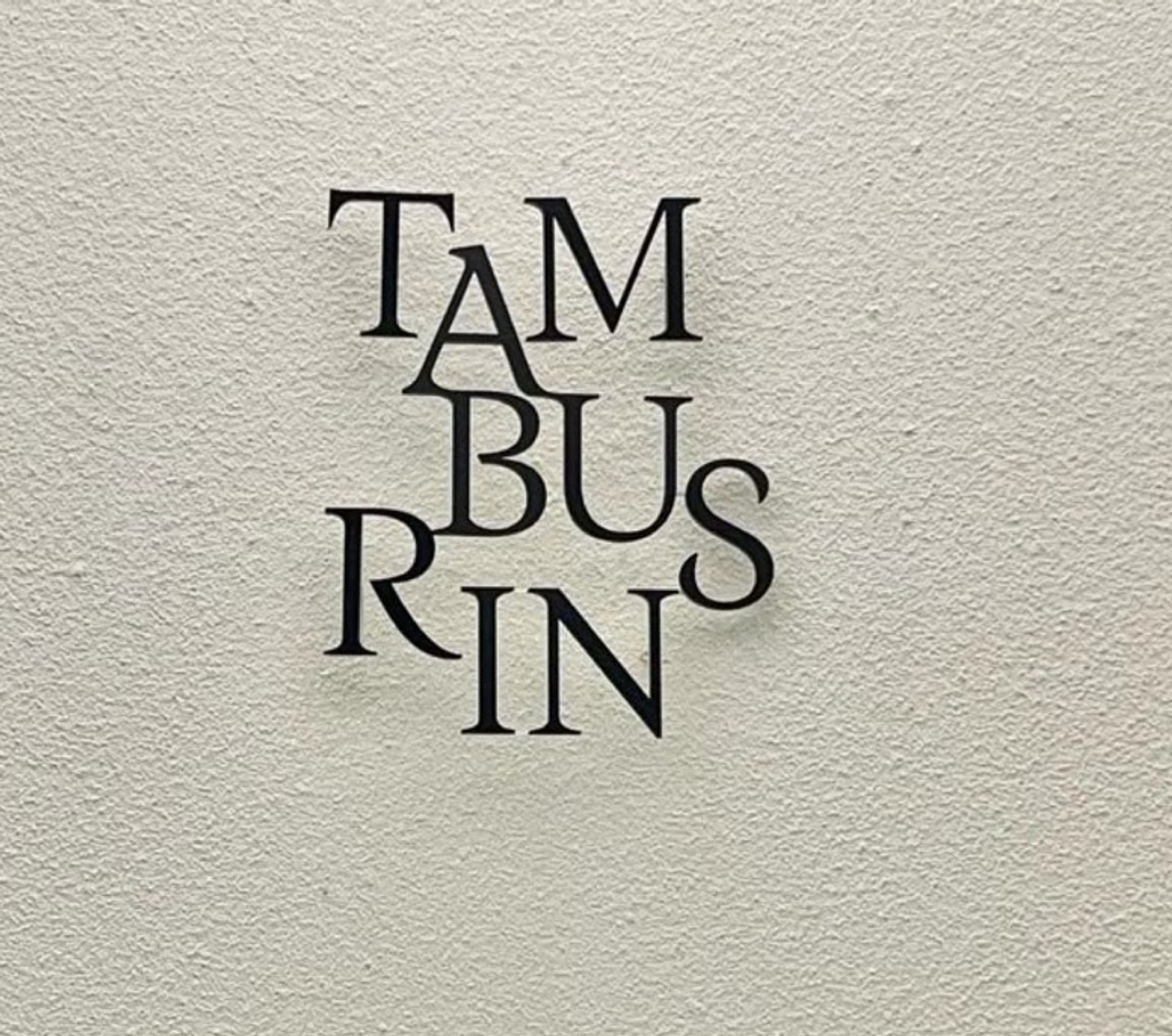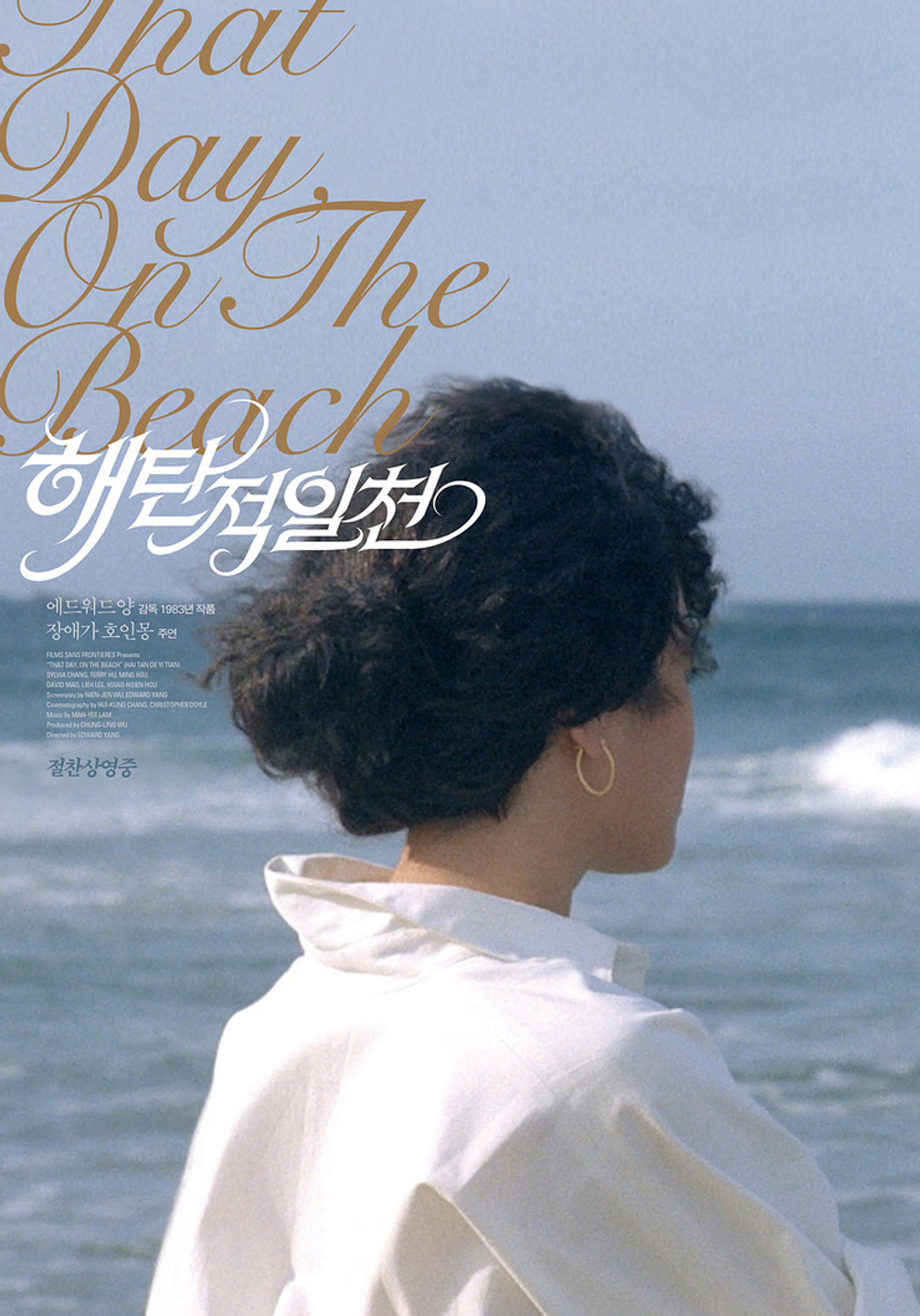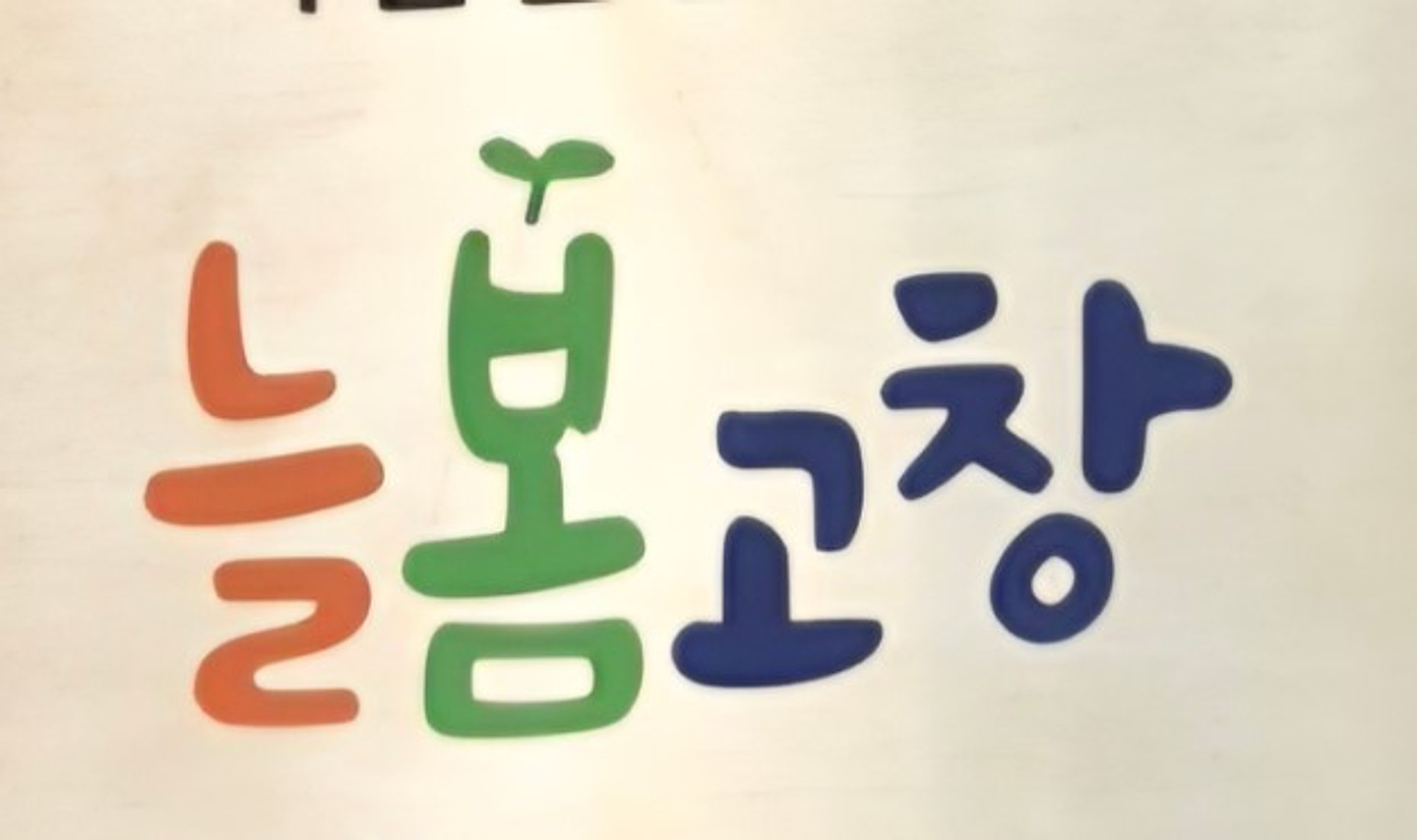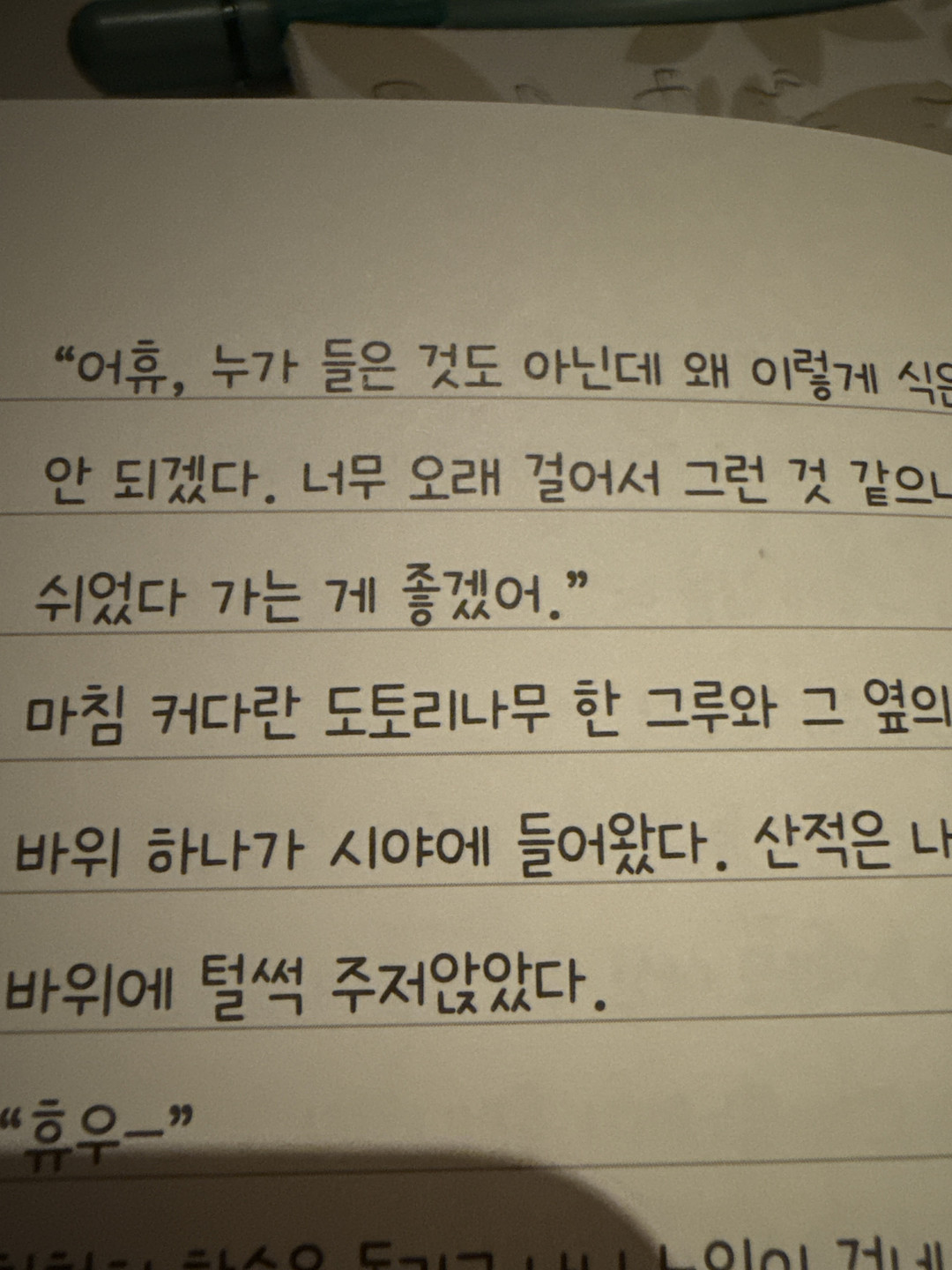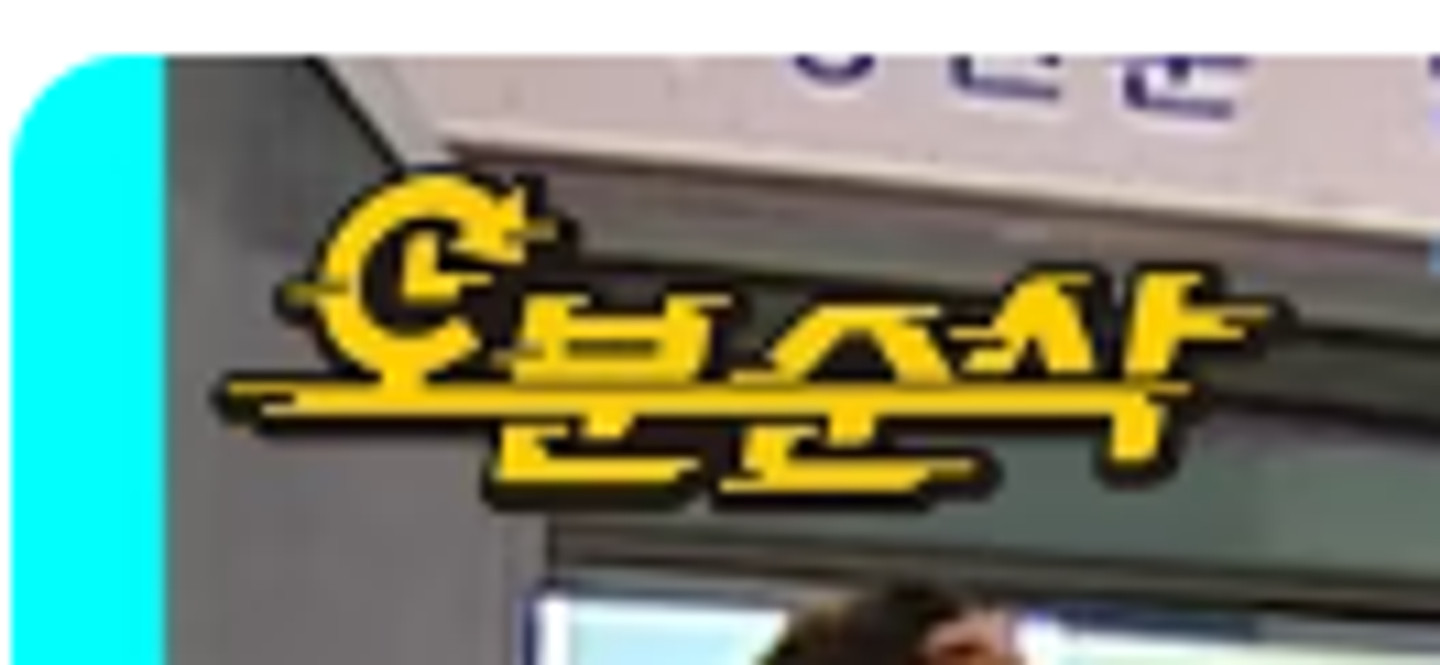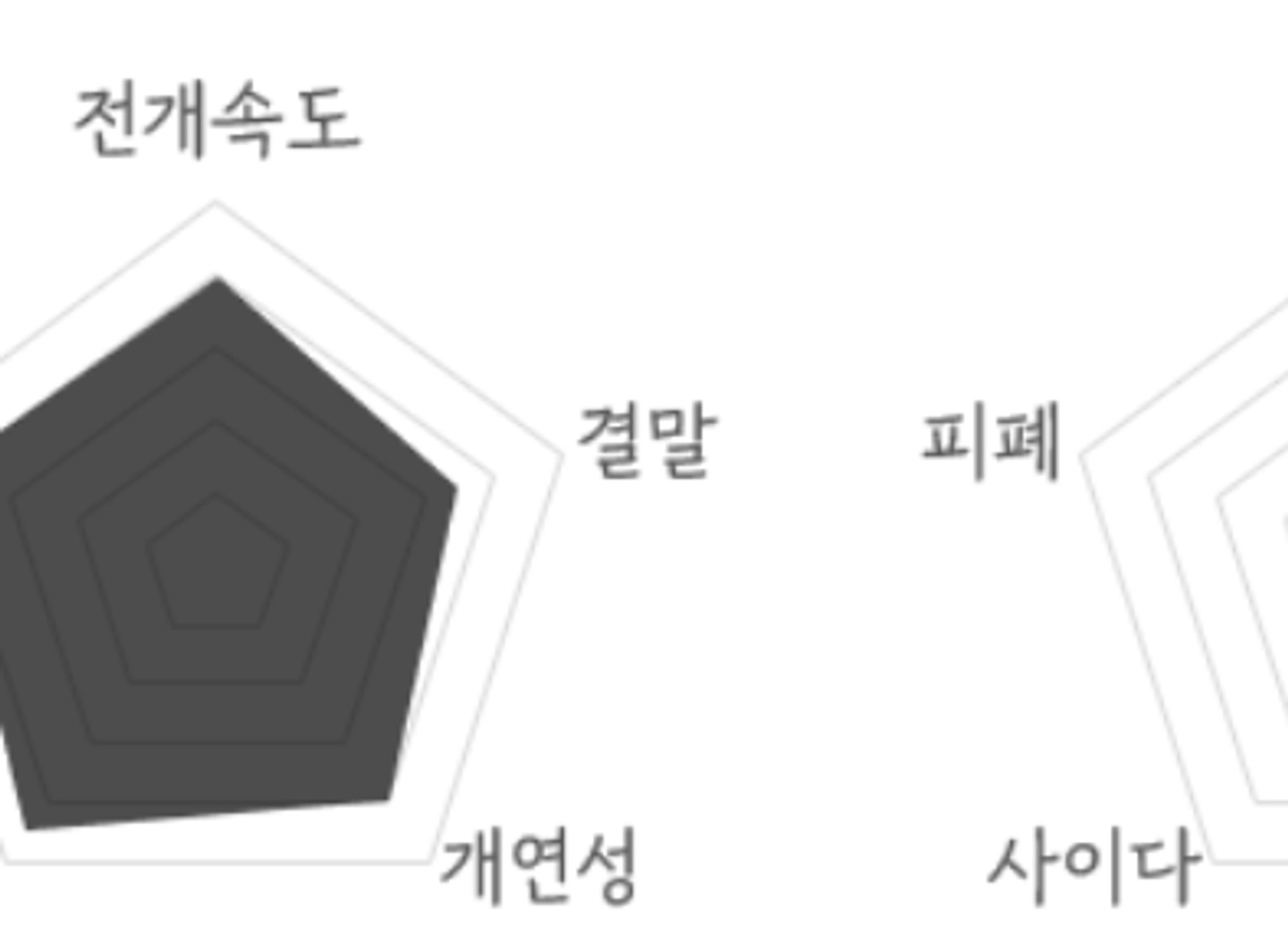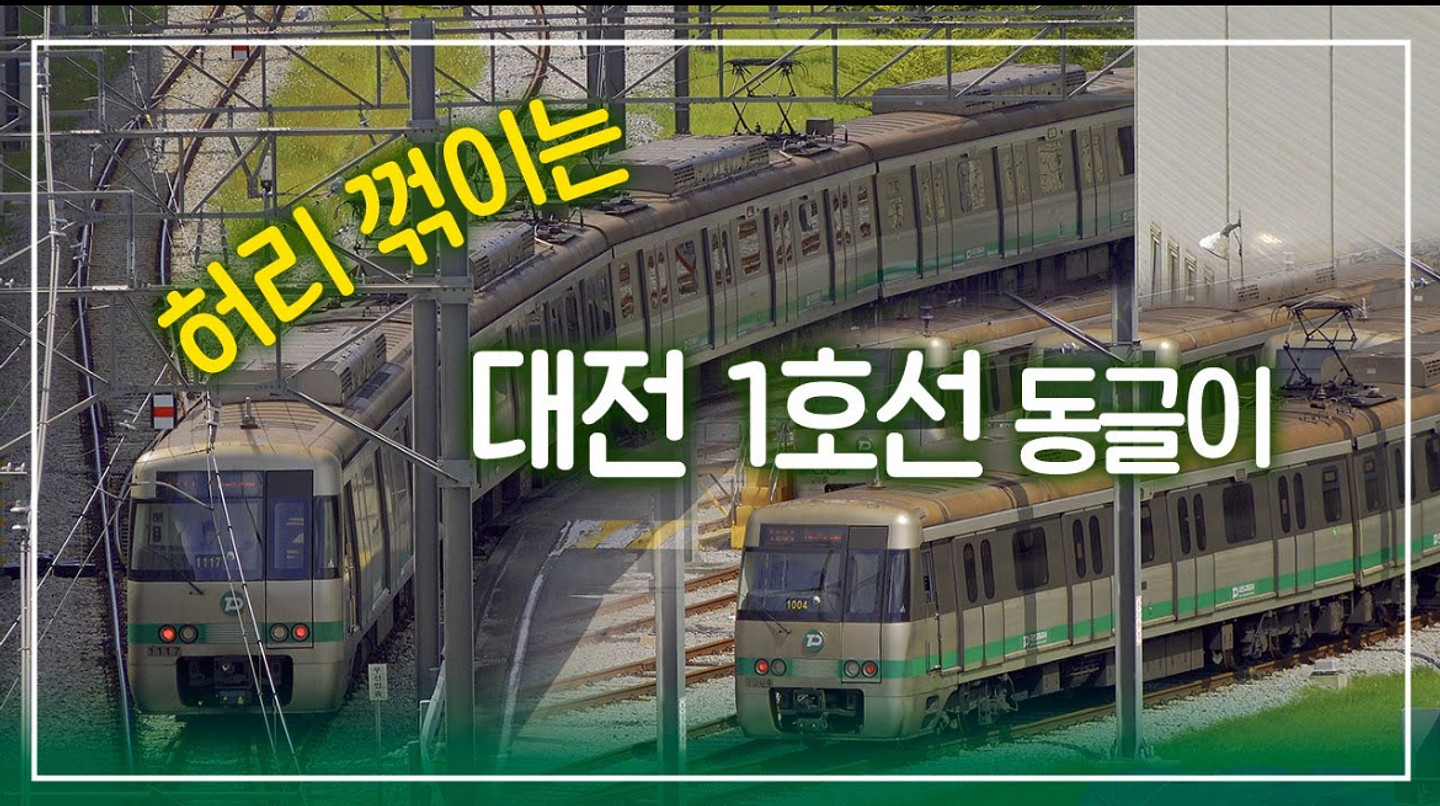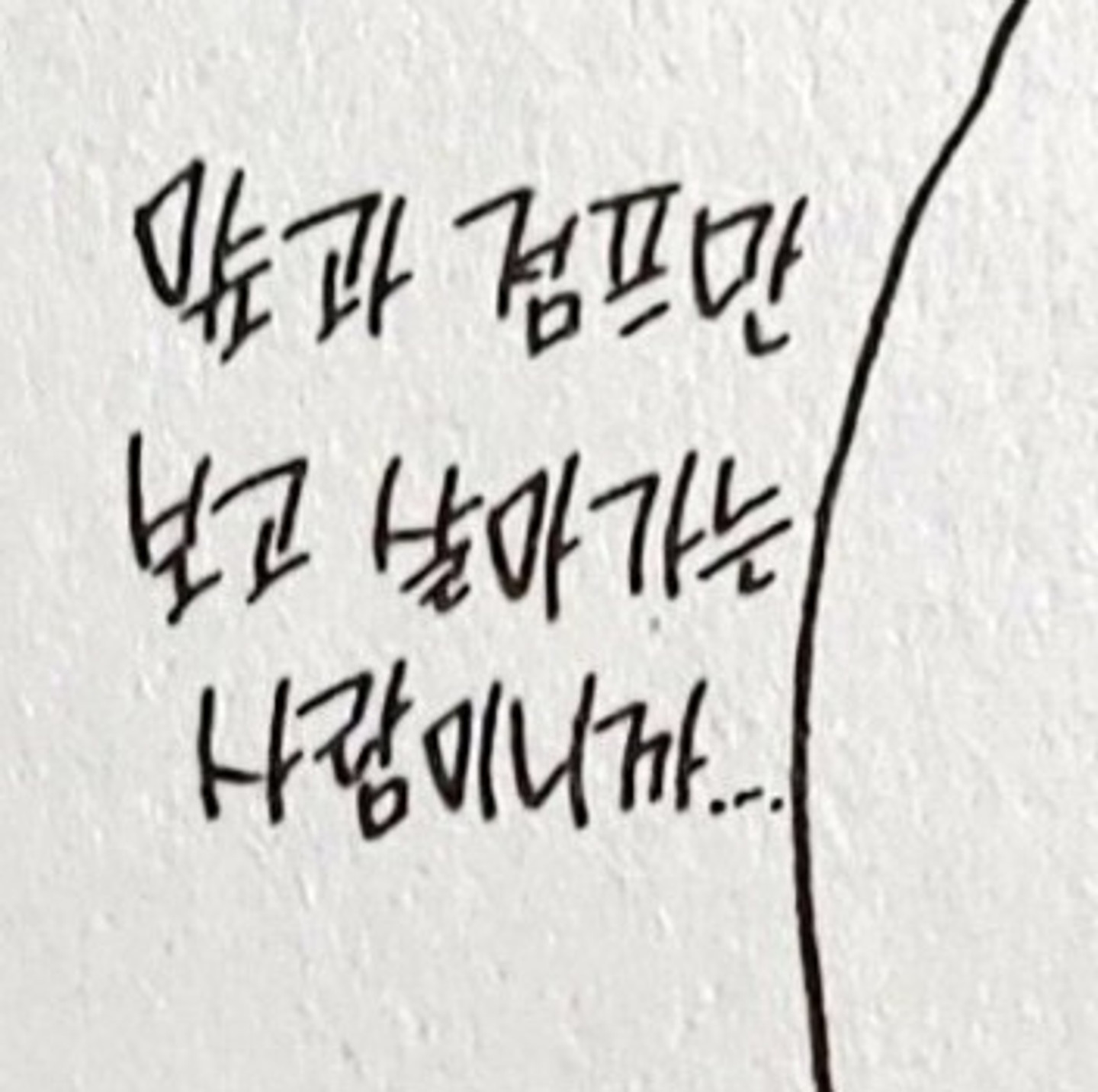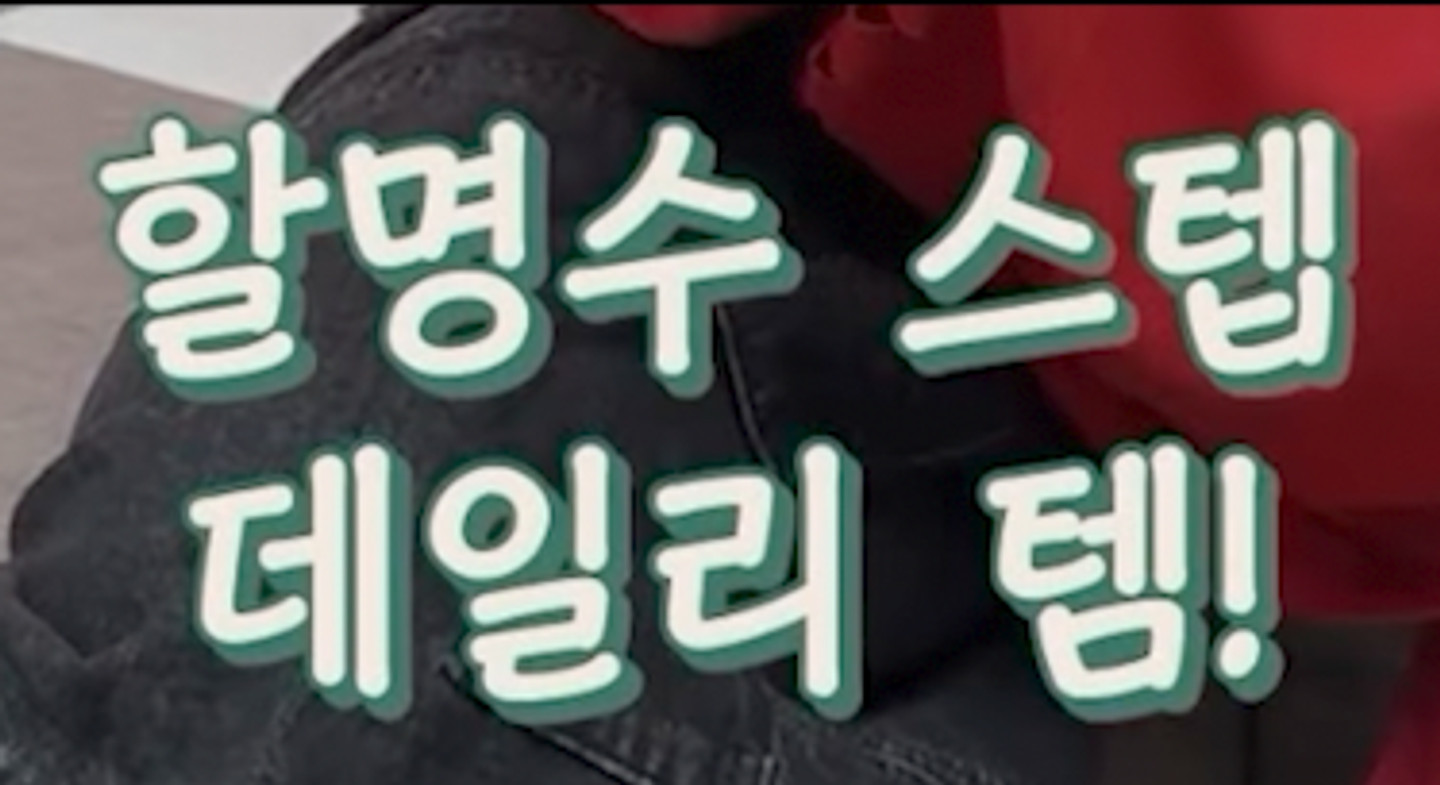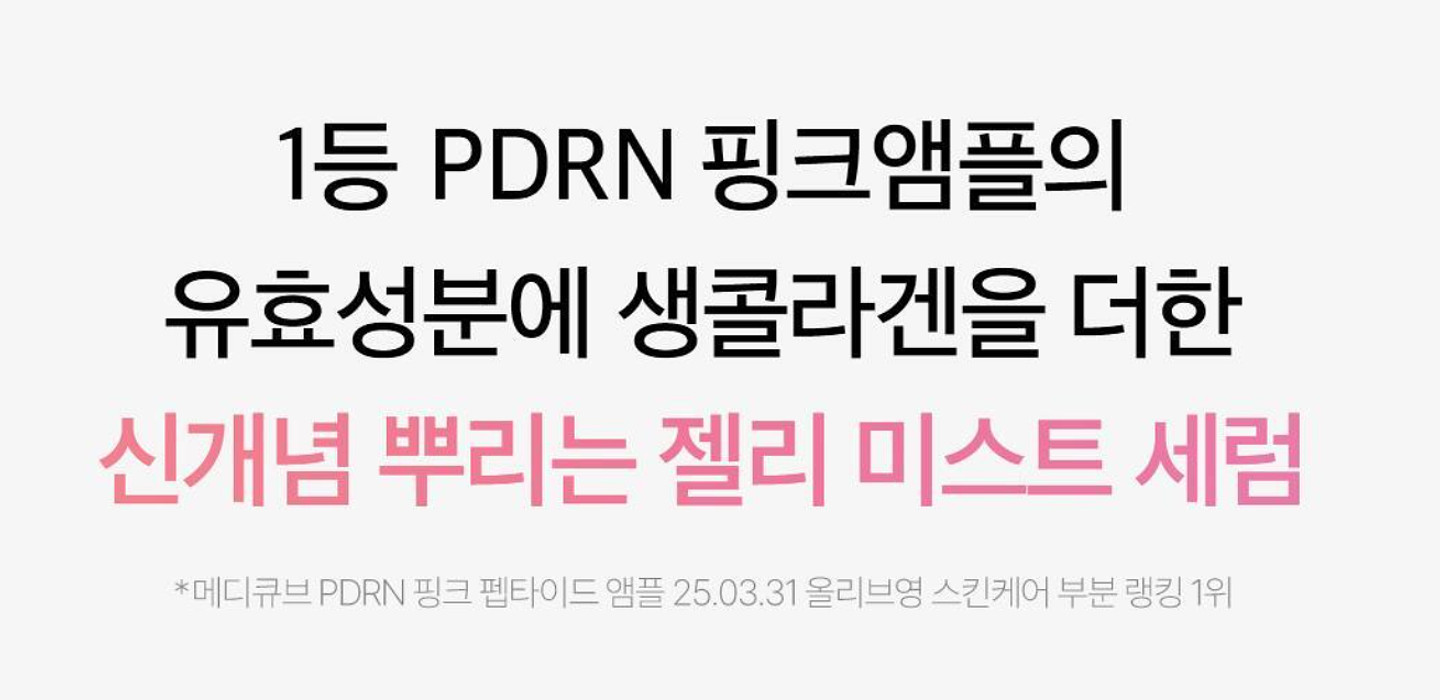
안녕하세요~ 이미지 속 폰트 정보 부탁드립니다.
헤드라인 폰트 인줄 알았는데 아니네요
이거 무슨 폰트인지 아시나요??? 급합니다ㅠㅠㅠㅠ
무슨 폰트인지 알고 싶습니다.
이 글씨체는 뭔가요?
그라운드시소 전시 <오늘의 정원> 폰트 궁금합니다!
그라운드시소 전시 <내일의 낙원> 폰트 궁금합니다!
유료 폰트라면 유사한 무료 폰트도 같이 추천해 주세요 ㅠㅠ
폰트 누무 귱금해오
궁금합니다! 항상 잘 찾아주셔서 감사해요
이 폰트 이름 뭘까요ㅠㅠ
엔딩크레딧이랑 비슷한듯도 하고..영화자막체 같기도 한데.. 아시는 분 계실까요?
받침에 있는 기역이 꺾여있는 손글씨 느낌 폰트 궁금해요
봉태규님 유투브에더 있는 폰트인데 뭘까요
폰트요? 미리 감사드립니다
이거 폰트이름 뭘까요ㅠㅠ
폰트가 너무 궁금하네요,,, 아시는분은 알려주세요 부탁드려요 ㅎㅎ
뮤슨폰트일까용??ㅠ
폰트 찾아주세요
어떵 폰트일까요ㅠㅠ 박다현체랑 비슷한데 다른느낌....
ai한테 물어봤는데 정답이 없네요... 너무 궁금합니다
이거 눈누에 잇는 폰트 같은데 이름 먼가요??
음악회에서 자주 보이는 고급 폰트입니다. (7은 일러스트레이터에서 추가 작업을 한 것 같아요. ) 2,6,9,7 이 묘한 통일성이 있구요. 숫자 0과 앨퍼벳 O도 묘한 공통점이 있어요. 이 폰트 많이 아실 것 같은데, 막상 찾으려니 힘드네요.
이거 무슨글씨체인지 아시는 분 계실까요..?? 비슷한거라도 좋습니다ㅠㅠ!!
이 폰트 뭘까요???
궁금해요 ㅠ
궁금해요 ㅜㅜ
화질이 안 좋긴 한데.. 무슨 폰트인지 알고 싶습니다..!
위에 노랑색 폰트랑 아래 흰색 폰트 무슨 폰트 사용했는지 알 수 있을까요?
위에 주황색 폰트랑 아래 궁서체 같은 폰트 어떤거 사용했는지 궁금합니다!
이거 무슨 글씨체인지 알 수 있을까요?
이 폰트 알고싶어여 ㅠㅠ
폰트이름 알려주세요~
글씨체 궁금해요!
이 영문 폰트 뭔가요?
이 폰트 이름 뭘까요?
폰트 알려주세요!!! ㅠㅠ
SK 채용 공고에 사용된 글씨체 뭘까요?
이거 무슨 폰트인가요?!
투어스 자컨 [TWS:CLUB] PC방탈출 #1 EP.12 오프닝입니다.. 무슨 폰트인가요?
무슨 폰트인지 아시는 분 계신가요?
무슨 폰트인지 궁금해요. 나무위키에 있는 노선 로고 이미지입니다.
무슨 폰트일까요? 낭만있구미체랑 비슷한데 다르네요
'프'가 굉장히 납작한데, 정확히 어떤 폰트인가요?
이 폰트 이름이 뭘까요.... 210 단비는 아니던데........ 제발 찾아주세요....
이거 무슨 폰트인지 궁금합니다 돋움계열스러운데